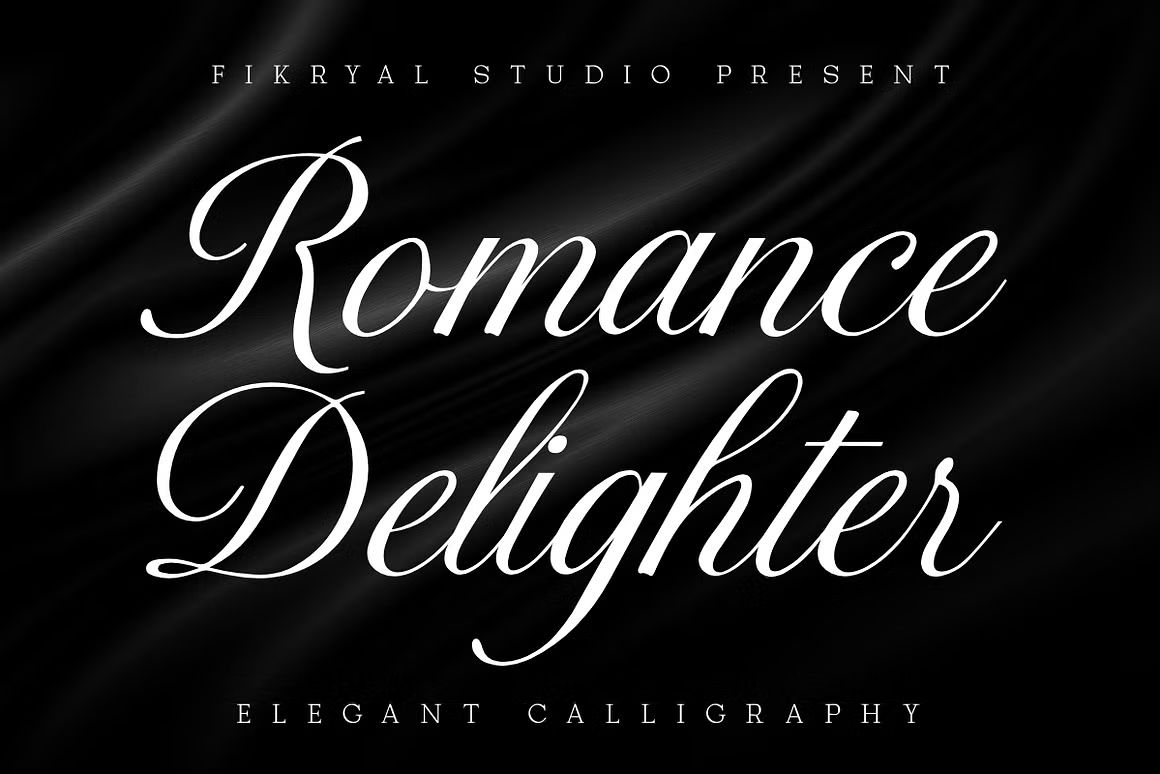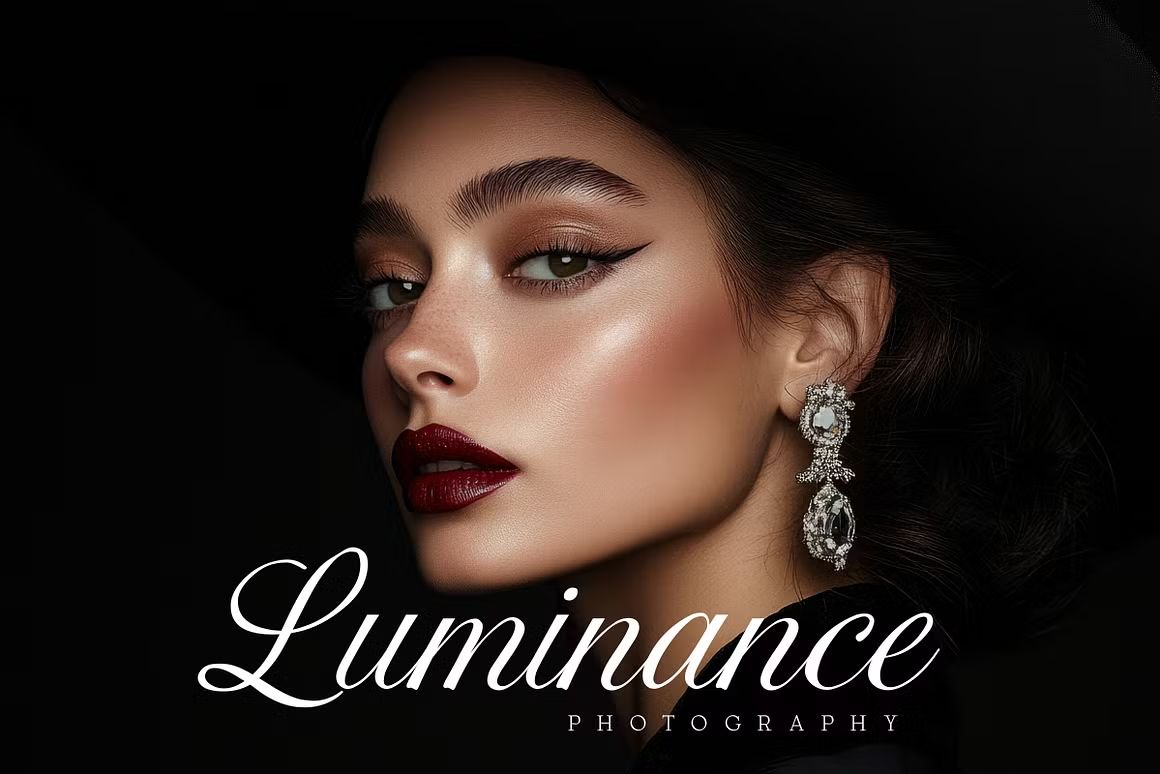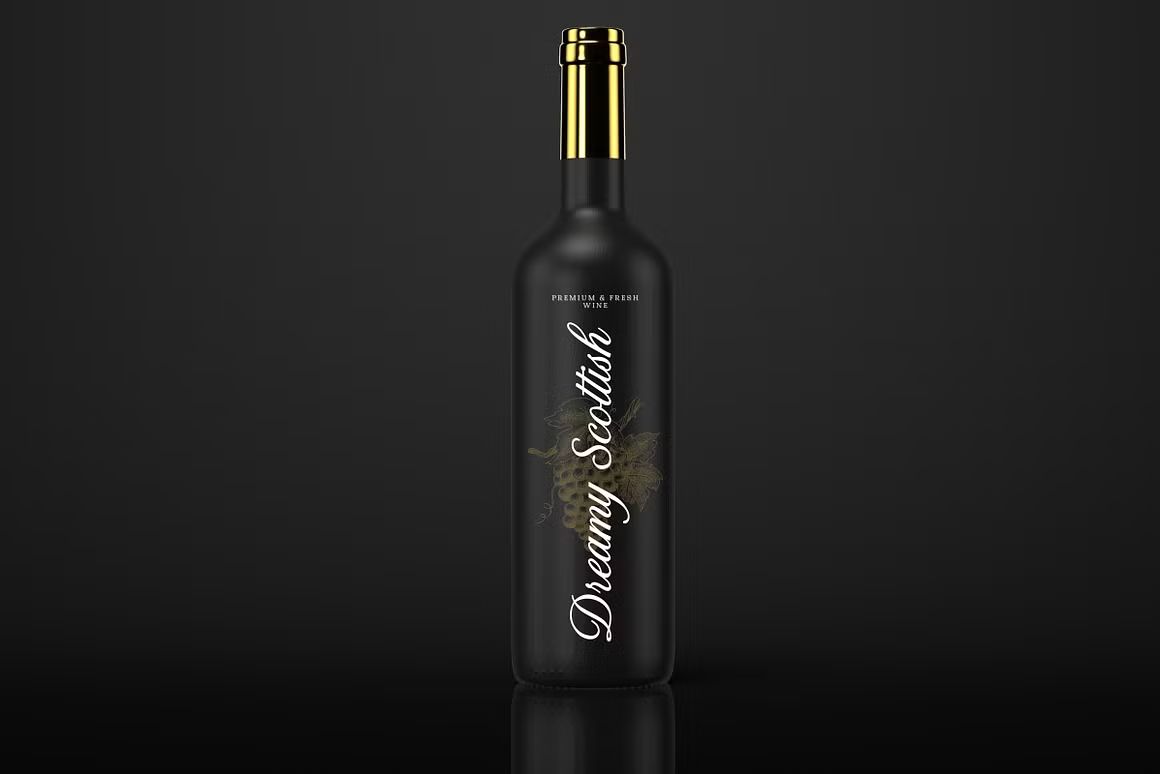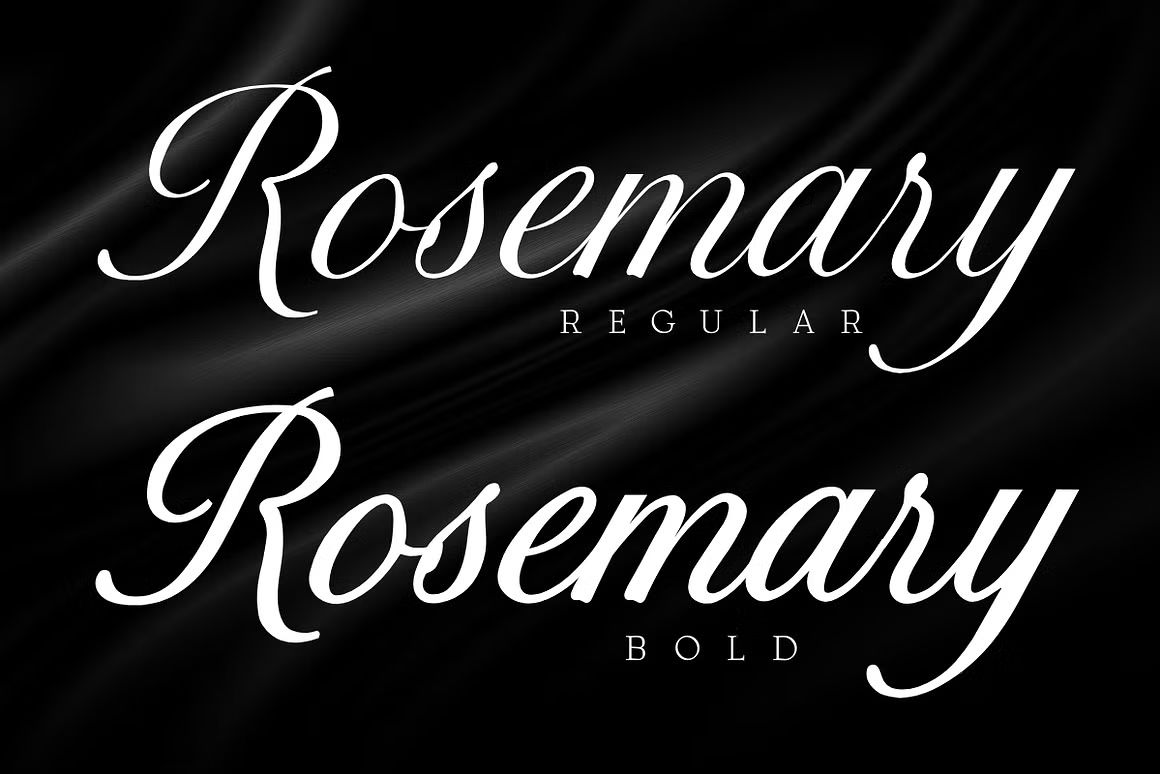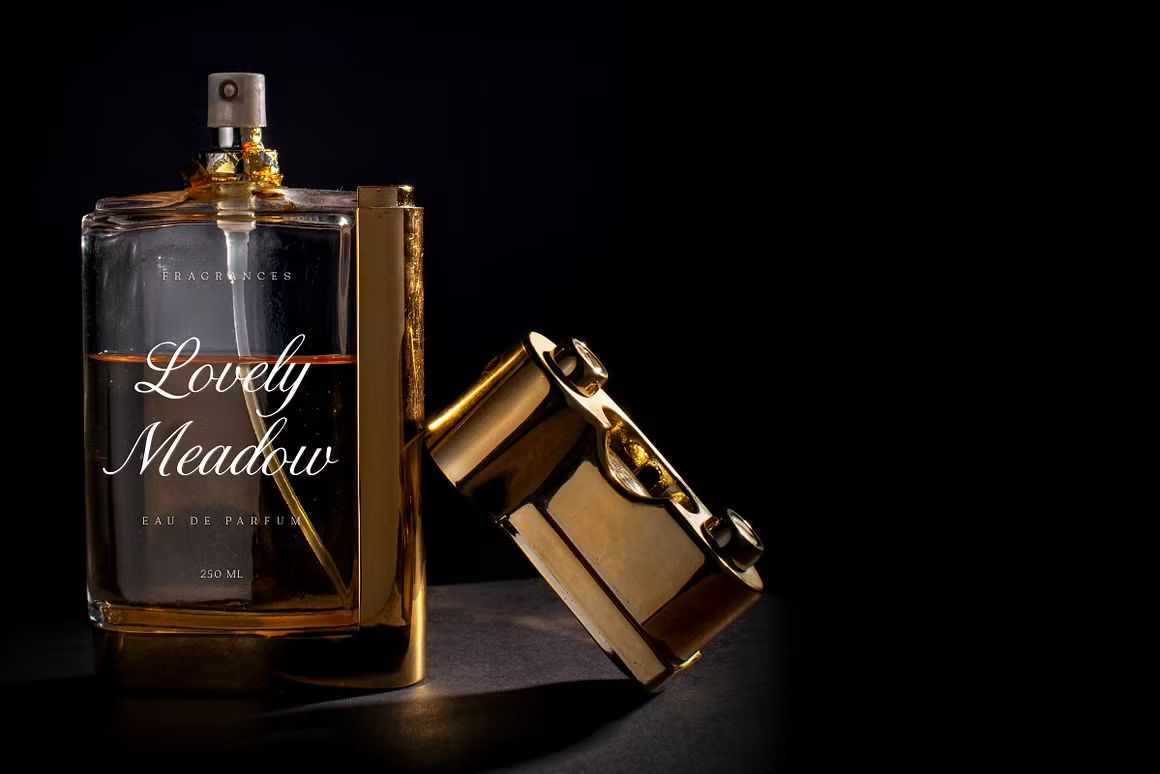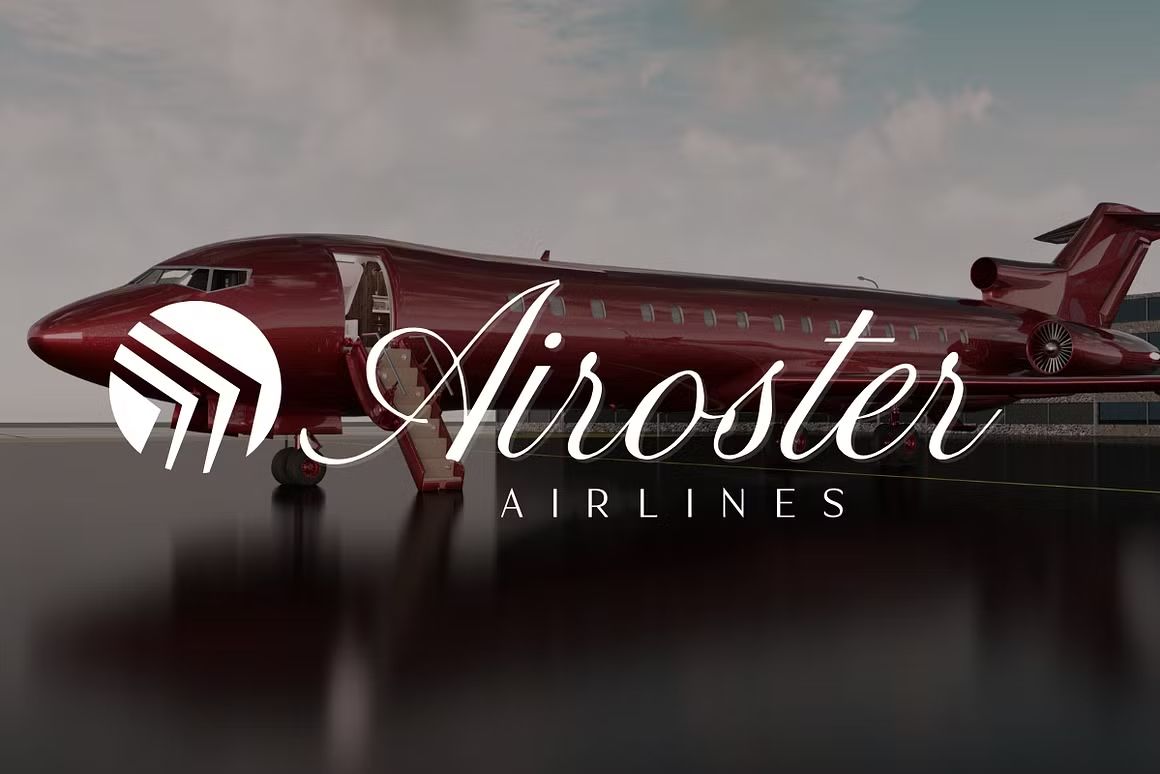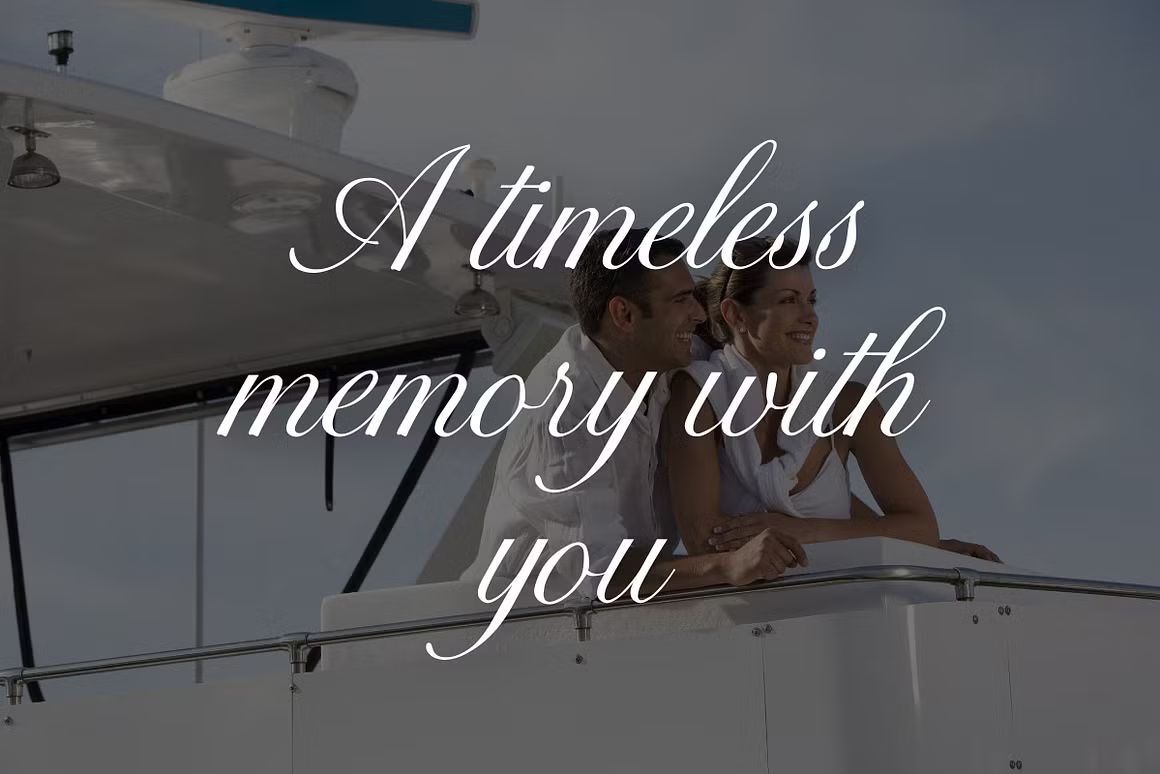
Romance Delighter – Script Font
Romance Delighter adalah font script romantis bergaya tulisan tangan elegan. Cocok untuk wedding, logo feminin, dan desain cinta. Format OTF/TTF/WOFF, siap digunakan.
Romance Delighter adalah font script yang anggun dan romantis, dengan gaya tulisan tangan yang halus dan elegan. Didesain untuk menyampaikan kehangatan dan keindahan, font ini sangat cocok untuk undangan pernikahan, logo feminin, kutipan romantis, kemasan produk, dan berbagai proyek desain bertema cinta atau keintiman. Setiap huruf mengalir dengan indah, menjadikan tampilan desain lebih personal dan menawan.
• Gaya script elegan dengan sapuan romantis
• Ideal untuk wedding, branding feminin, dan kutipan cinta
• Lengkap dengan huruf besar, kecil, angka, simbol, dan ligatur